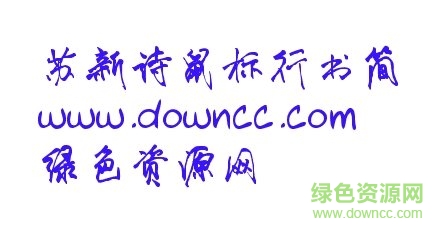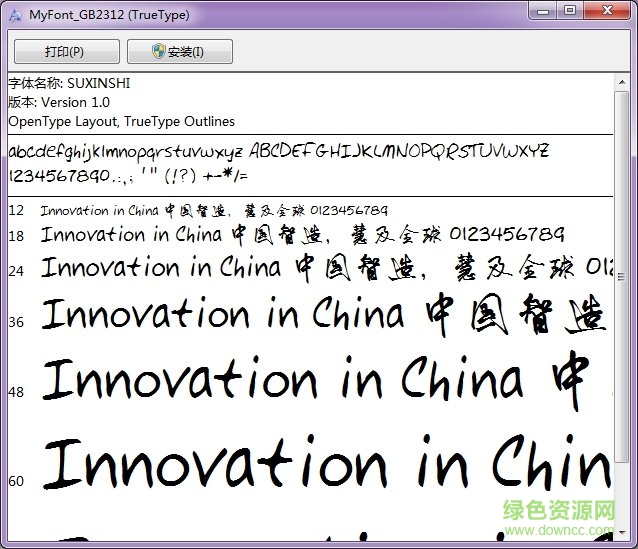
蘇新詩鼠標(biāo)行書簡(jiǎn)是一款以行書為模板的精美藝術(shù)手寫字體,給人字跡沉穩(wěn)大氣的莊重體驗(yàn),兼具行書飄逸灑脫的清揚(yáng)之美,綠色資源網(wǎng)歡迎大家免費(fèi)下載使用!
蘇新詩鼠標(biāo)行書,采用鋼筆書法會(huì)做,字體個(gè)性張揚(yáng)、不拘一格,整體效果十分出色,可以應(yīng)用于各類廣告宣傳、電子賀卡制作、明信片制作等設(shè)計(jì)領(lǐng)域!
蘇新詩,網(wǎng)名以歌,方正柳體字庫制造者,獨(dú)立開發(fā)整套中文字庫第一人,曾發(fā)布“蘇新詩卵石體”、“蘇新詩鼠標(biāo)行書”、“蘇新詩毛糙體”等電腦字庫。擅長書法、繪畫、攝影、平面設(shè)計(jì)。自幼習(xí)書,遍臨各帖;繪畫主攻人像漫畫;攝影以風(fēng)光建筑為主。